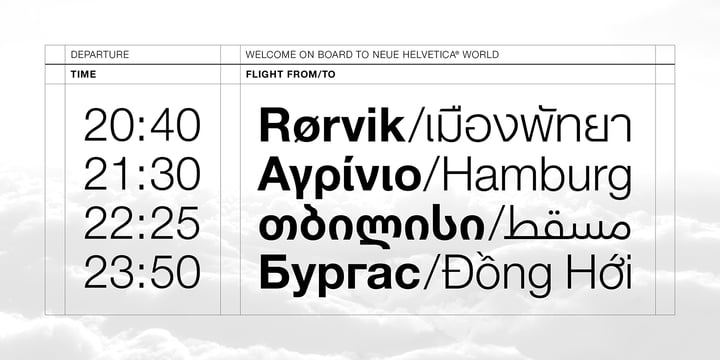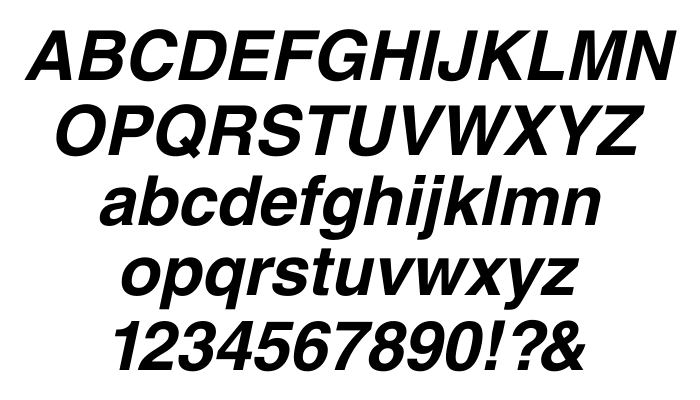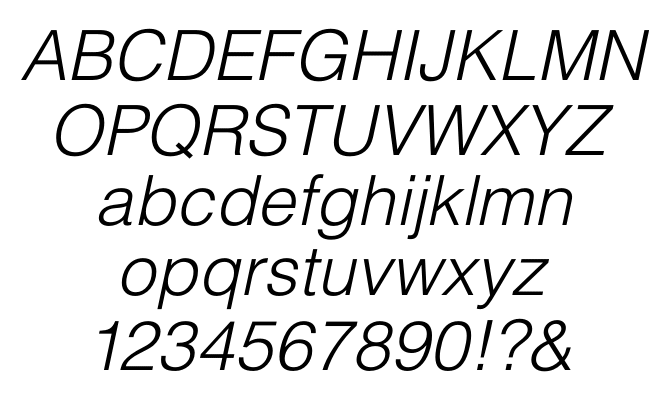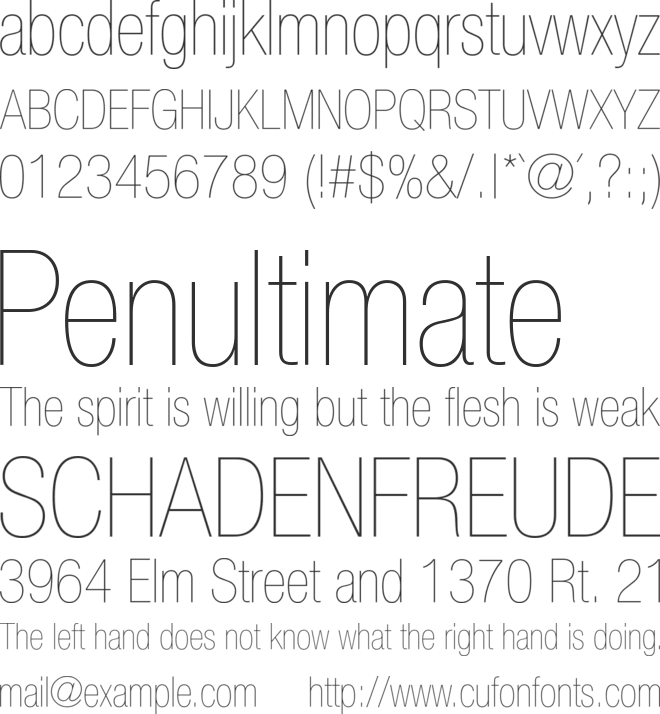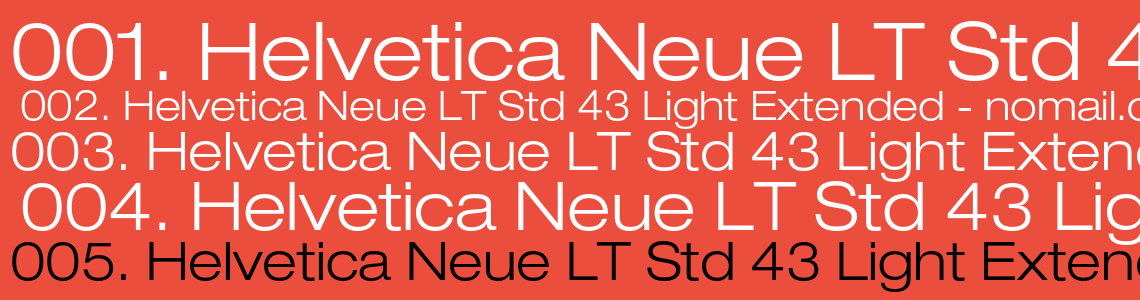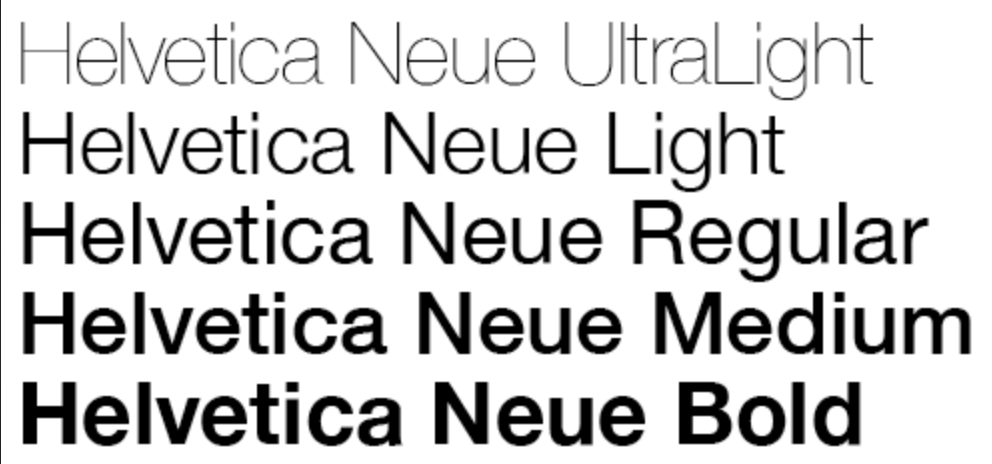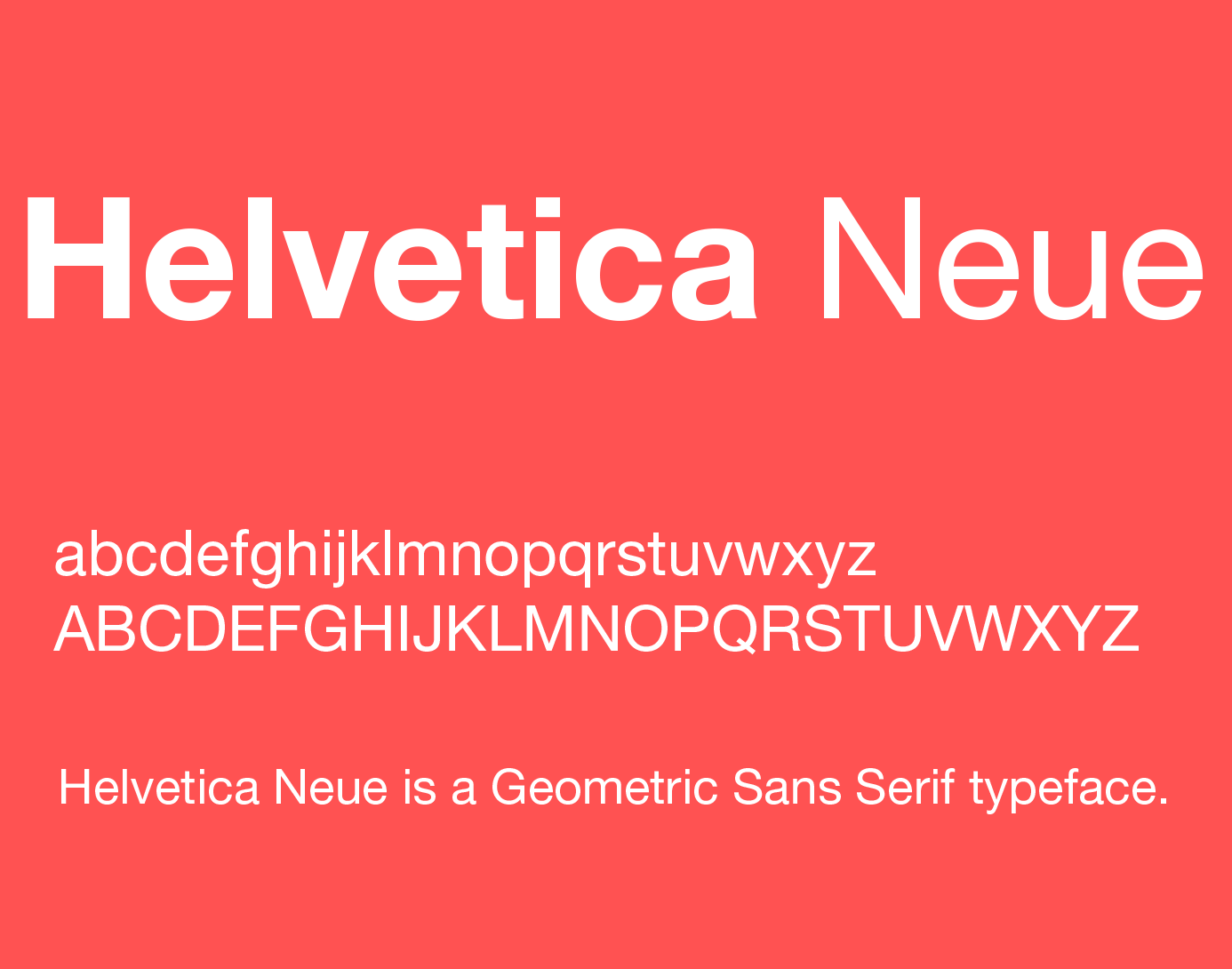
Шрифт Vanta выполнен достаточно непрофессионально, но поскольку время от времени всплывает, необходимо сказать о нем несколько слов. Он имеет 5 прямых начертаний (Extra Thin, Thin, Regular, Bold, Extra Bold). Это была попытка сделать кириллический прямой курсив. То есть вместо буквы Д (PT Pragmatica, Rus.) взята латинская G (Vanta, Lat.; д — Vanta, Rus.), вместо И, П, Т (PT Pragmatica, Rus.) использованы латинские U, N, M (Vanta, Lat.; и, п, т — Vanta, Rus.). Особенно «хороша» буква Л, вместо которой применено зеркальное отражение буквы N, это уж совершенно ни на что не похоже. В свое время в Болгарии были подобные попытки как бы латинизировать строчные буквы в кириллице, но у нас они никогда не имели успеха, хотя были гораздо профессиональнее. Остальные кириллические буквы Vanta, которые нельзя было вытащить из латиницы, а надо было рисовать, такие, как Д, Ж, И, Й, Л, У, Ф, Ц, Э, Я выглядят не менее хуже, поэтому нет необходимости объяснять почему они неправильные.
- Helvetica Neue Cyrillic (Linotype, дизайнер А. Чекулаев, 1998). (рис.28)